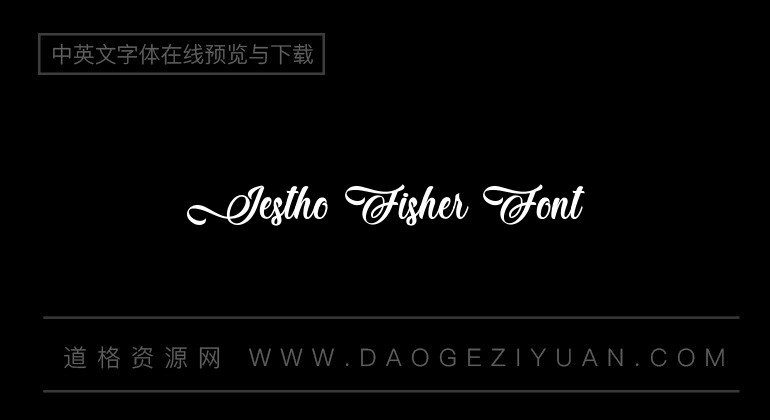
Jestho Fisher Font 是一种手写风格的英文字体,它的设计师是一位叫做 Jestho 的艺术家。这种字体的特点是自然、流畅,具有一定的装饰性,适合用在一些手写类的设计中,比如卡片、名片、海报等等。 Jestho Fisher Font 包含了 500 多个字符,包括大写字母、小写字母、数字和标点符号,同时还包含了一些特殊字符和连字。这种字体可以在电脑上安装并使用,也可以在一些设计软件中使用,比如 Adobe Photoshop、Illustrator 等等。内容介绍
Jestho Fisher Font是一款非常不错的手写艺术字体,具有很好的视觉感,适合于文化类的宣传设计、商业类品牌的广告和产品包装设计以及个性化文字排版等较多场景。